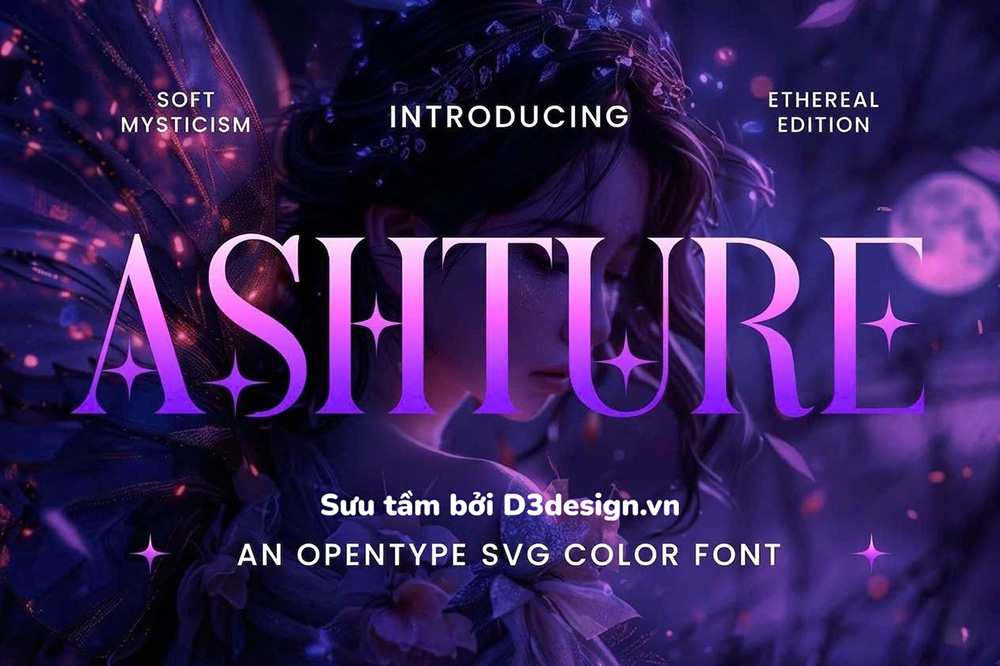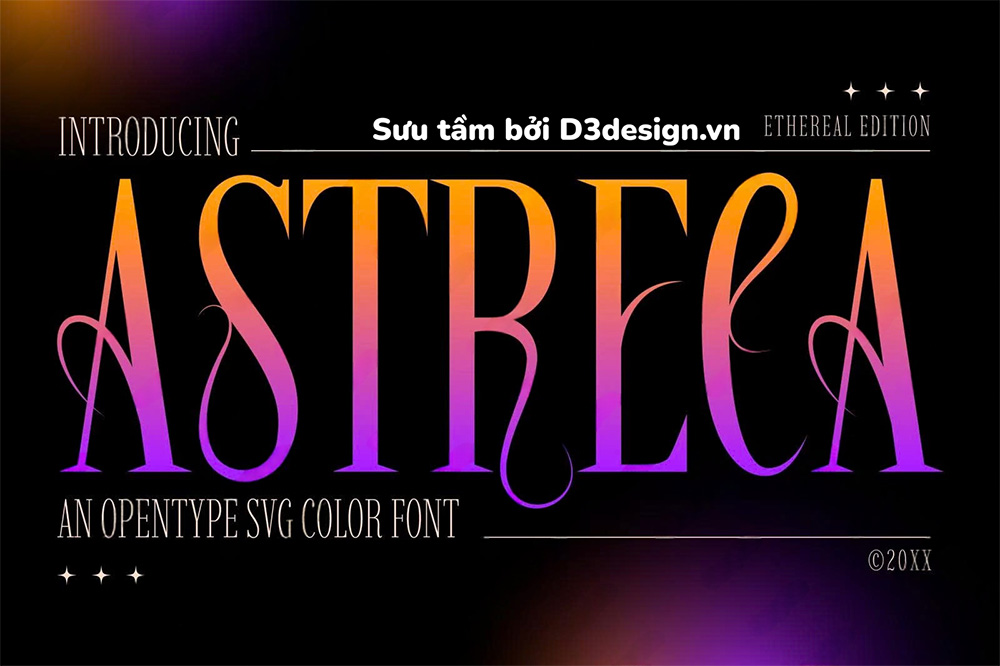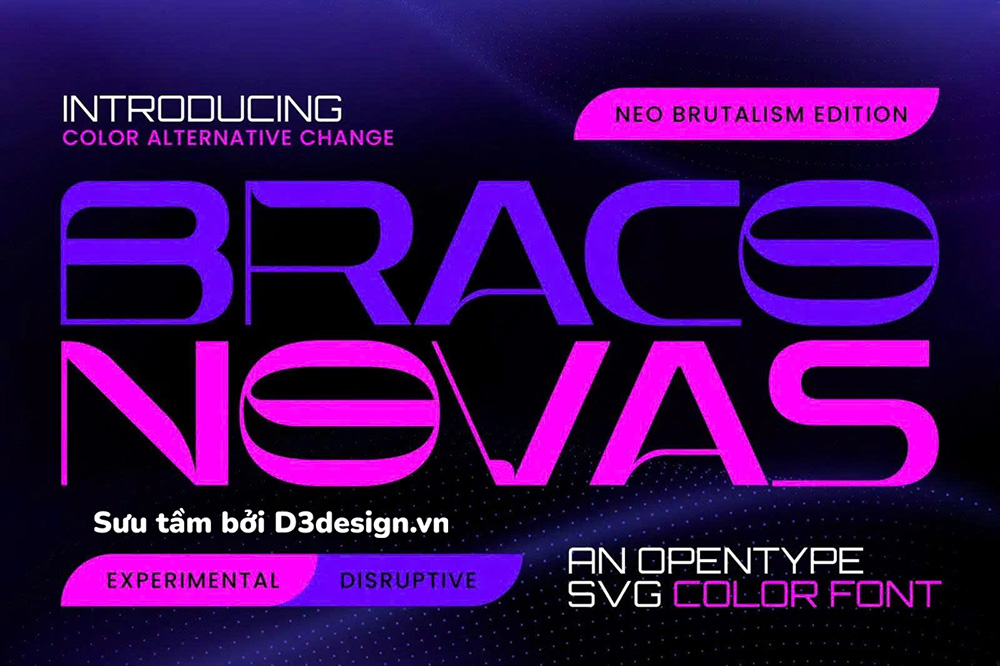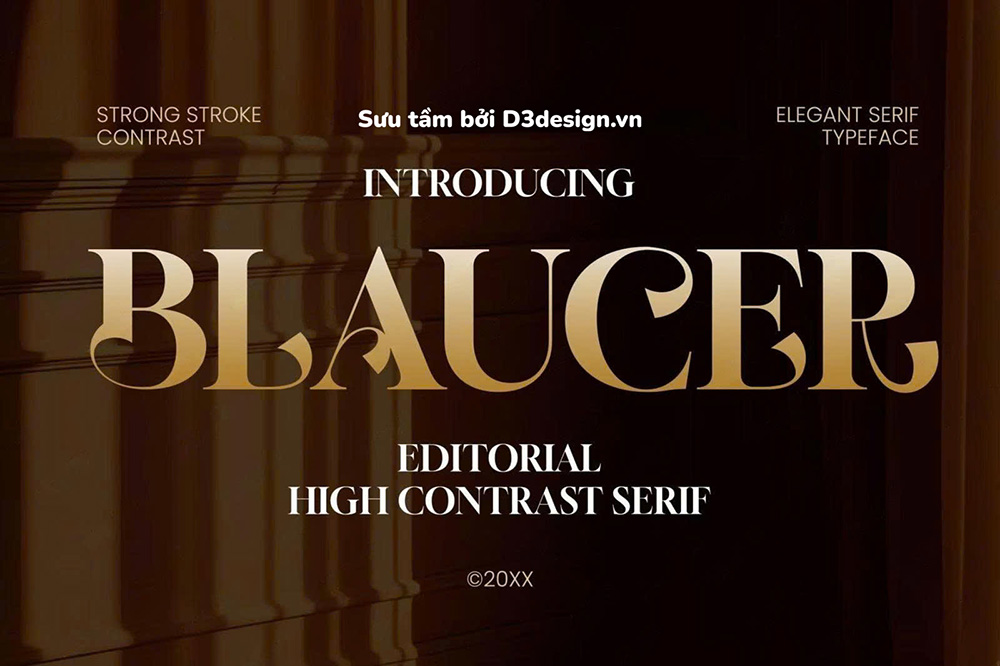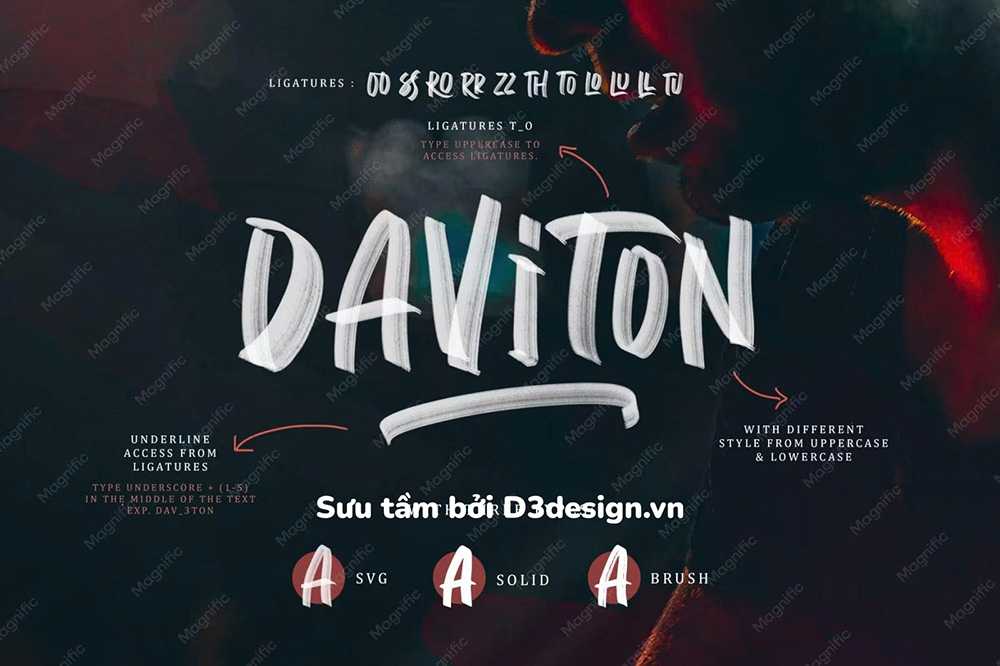
Trong thiết kế đồ họa, font chữ không chỉ là công cụ hiển thị nội dung mà còn đóng vai trò quan trọng trong việc truyền tải cảm xúc và phong cách. Việc lựa chọn đúng font có thể giúp thiết kế của bạn trở nên chuyên nghiệp và ấn tượng hơn rất nhiều.
Trong bài viết này, mình đã chọn lọc 5 font chữ mới, siêu đẹp với nhiều phong cách khác nhau – từ hiện đại, tối giản đến nghệ thuật sáng tạo – phù hợp cho mọi nhu cầu thiết kế của bạn.
Không phải cứ nhiều font là tốt. Quan trọng là font phù hợp và dùng hiệu quả. Bộ font này được chọn dựa trên những tiêu chí quan trọng:
-Tính thẩm mỹ cao: Hiển thị đẹp trong cả tiêu đề và nội dung
-Dễ sử dụng: Không cần chỉnh sửa phức tạp
-Đa dụng: Phù hợp từ thiết kế mạng xã hội đến in ấn
-Tối ưu workflow: Giúp bạn tiết kiệm thời gian thiết kế.